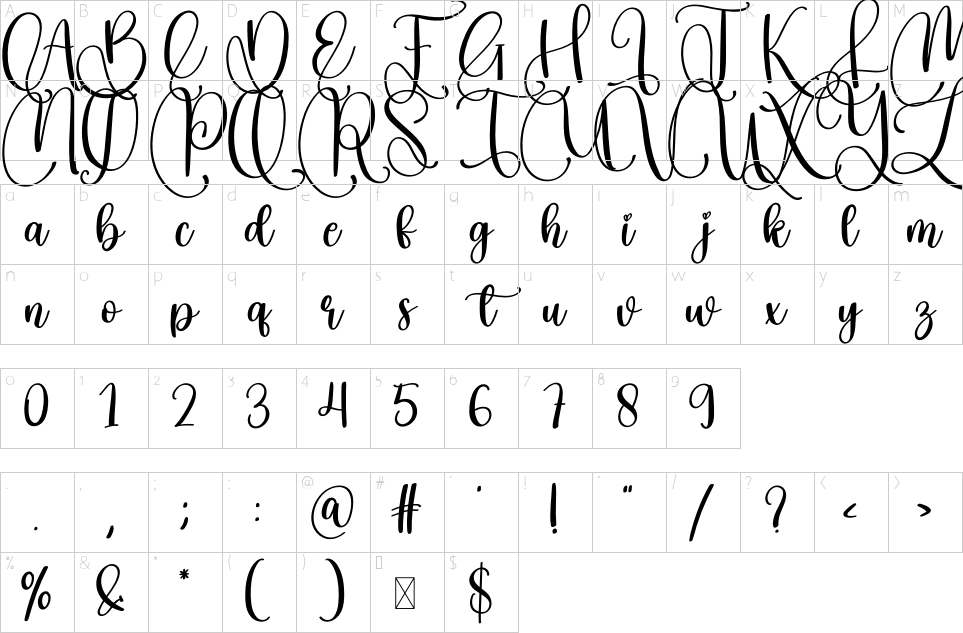
A Mother Font é uma fonte gratuita que oferece uma aparência elegante e moderna, perfeita para qualquer projeto de design. Ela foi projetada pelo criador anonimo e seu design está disponível para download tanto em versão Windows quanto Mac. Esta font é uma excelente opção para aqueles buscando um visual atraente sem precisar gastar dinheiro. Com o Mother Font, você pode trazer um toque sofisticado a qualquer tipo de texto, seja em um design de site ou uma simples publicação de redes sociais. Apenas 452 pessoas tiveram o privilégio de baixar esta font, tornando-a ainda mais valiosa e exclusiva. Se você está procurando por uma opção de fonte gratuita que ofereça um bom equilíbrio entre estética e praticidade, a Mother Font é definitivamente uma fonte que vale a pena dar uma olhada.